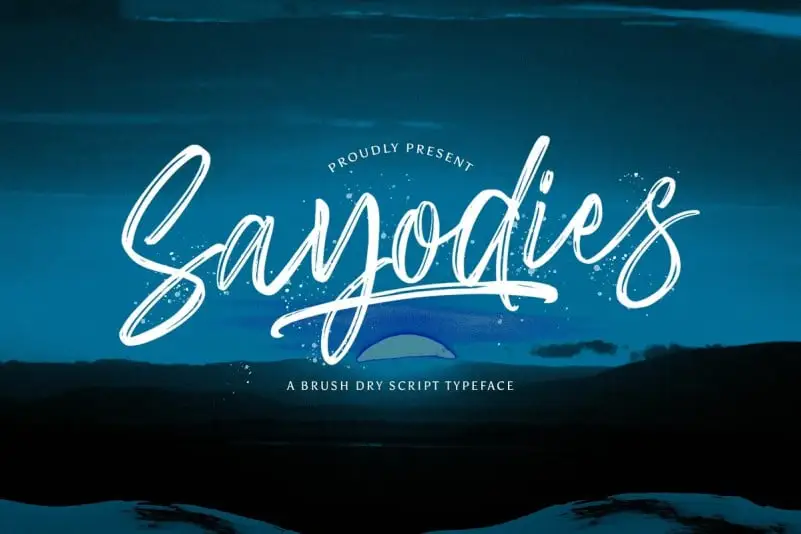
Sayodies Brush Font – Download Grátis
A Sayodies Brush Font é uma deliciosa curva do tempo do mundo da tipografia, escrita casualmente e rapidamente com as ferramentas mais simples – pinceladas no papel. Cada letra nascida de formas queimadas e incisadas por mãos artísticas, revelando um estilo atemporal e único perfeito para qualquer aplicação gráfica. Perfeita para branding, logomarca, convites, citações, design de roupas, embalagens de produtos, mercadorias, títulos de jogos e até mesmo em estilos infantis. Esta font é um verdadeiro tesouro para designers que buscam uma tipografia sofisticada mas com uma pitada leve e descontraída. Ideal para capas de livros ou qualquer outro projeto onde você deseja criar um design especial, único e cativante. Adquira a Sayodies Brush Font hoje e enriqueça seu portfolio com esse recurso gráfico que irá transformar suas criações em algo tão especial quanto ela mesma.